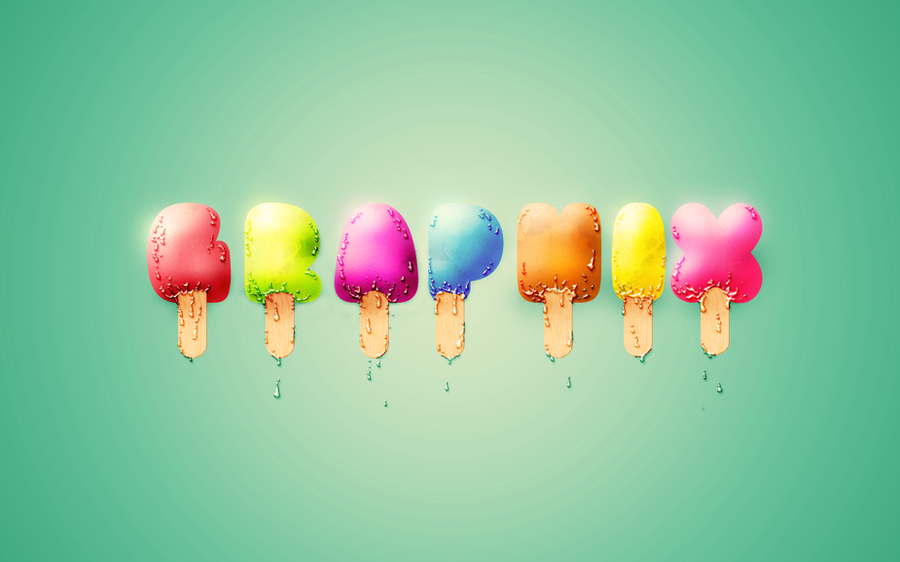
Bueno volviendo a las andanzas del abstract, espero les sea de su agrado!Aclaracion: un abstract es todo aquello que no existe en la realidad y no puede ser distinguido como algo natural por eso una font sola tambien abstract y a la vez un diseño de tipografia xD
eso con q lo creastes con illustrador? o puro PS D: o cinema 4 XD
puro photoshop, lo hice con texturas, y muchas opciones de capas xD